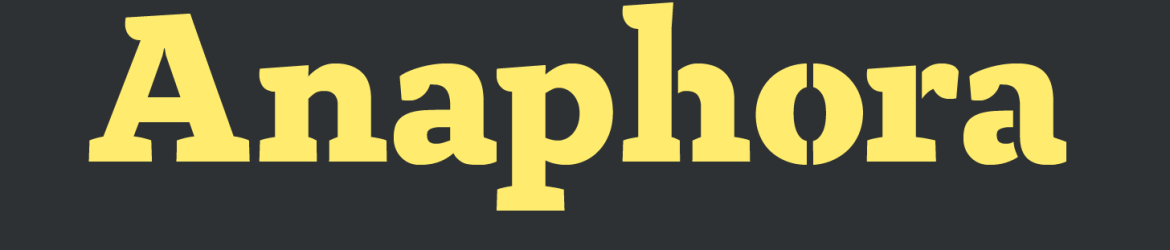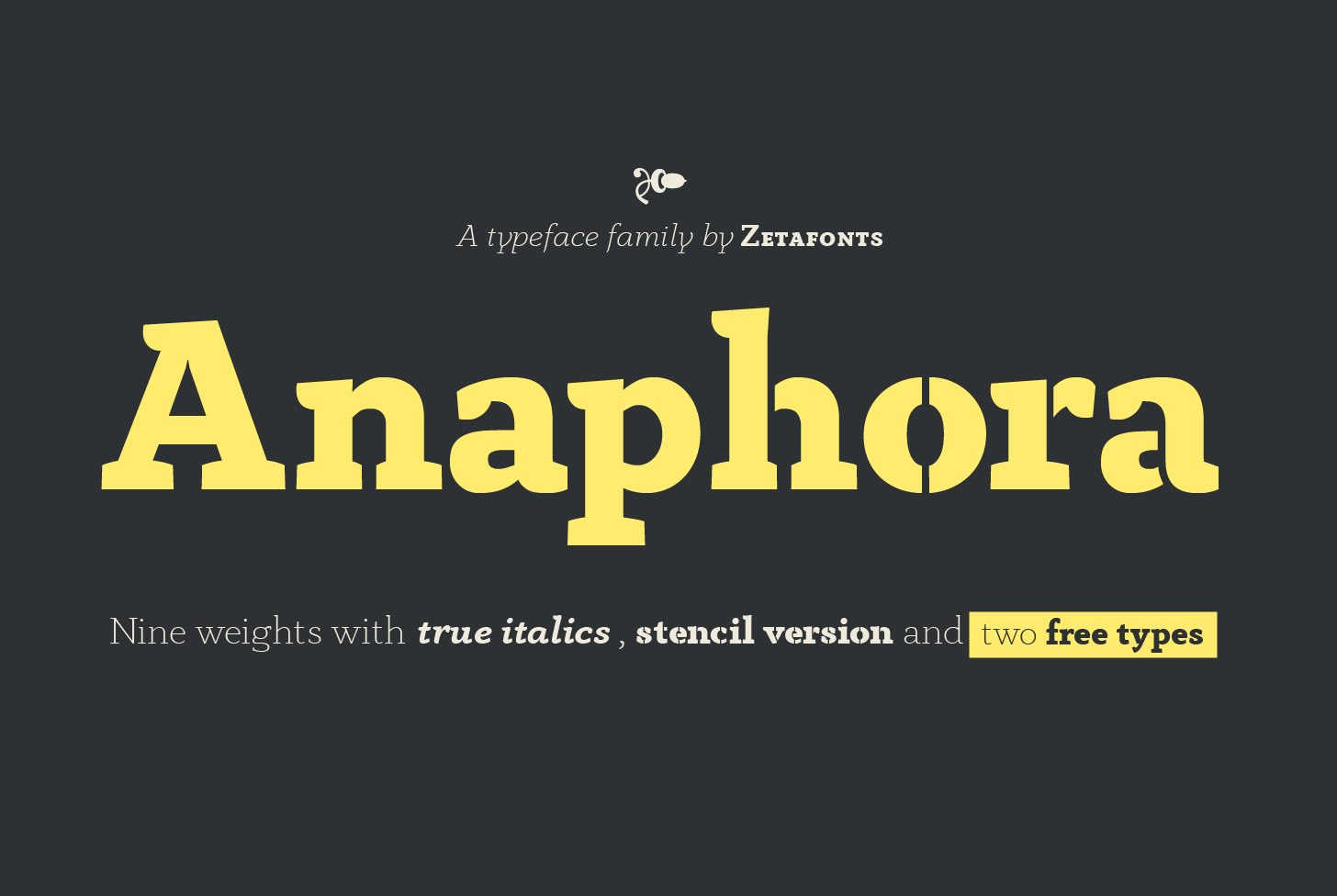
Anaphora Font Family – Fonte Grátis
Anaphora Font Family
Anaphora é uma nova família serif que acaba de ser lançada para ajudar a personalizar seus projetos de texto com um estilo único e sofisticado. Desenhada pelo talentoso Hamilton, Anaphora oferece uma rica experiência visual através da sua família de caracteres gêmeos, desde os mais finos até aos mais grossos. Este tipo de fonte é perfeitamente adaptável para uso tanto em editoriais quanto em campanhas publicitárias. O que torna Anaphora ainda mais especial são seus traços de parágrafo curvados, oferecendo um estilo elegante que se mistura com o conforto e a leitura fácil de uma fonte serif. Os espaçamentos largos entre as letras e a altura pequena das x, ou seja, o x-height, tornam a legibilidade extremamente boa em tamanhos menores, enquanto os desenhos pouco convencionais e aprimorados mantêm o tipo forte e reconhecível mesmo nas aplicações maiores. Engajante e versátil, Anaphora é perfeita para qualquer projeto que exija estilo profissional e um toque de personalidade.